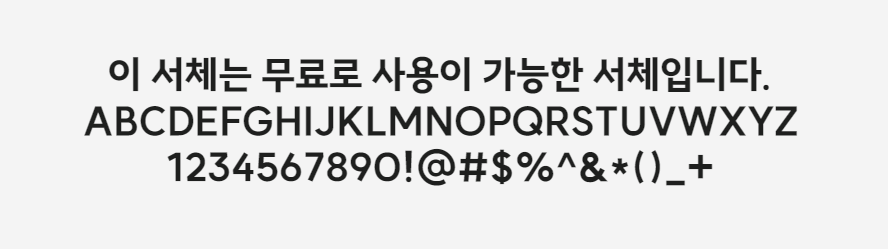
스위트체
스위트체는 현대적인 감각과 높은 가독성을 겸비한 무료 폰트입니다. 디지털 환경에서의 사용자 경험(UX)과 사용자 인터페이스(UI) 디자인에 최적화되어 개발되었으며, 간결하면서도 세련된 디자인이 특징입니다. 이 폰트는 정원, 직각, 직선, 사선 등 기하학적 조형 요소에 집중하여 디자인되었으며, 이는 스위트체가 간결하면서도 명료한 인상을 주는 데 기여합니다.
특히, UI 환경에서 헤드라인 폰트로 사용될 때 시선을 사로잡아 중요한 정보를 효과적으로 전달할 수 있도록 디자인되었습니다. 스위트체는 다양한 디지털 환경에서의 활용성을 고려하여 개발되었으며, 웹사이트, 앱, 디지털 출판물 등 다양한 매체에서 일관되고 세련된 디자인을 유지할 수 있도록 지원합니다.
다양한 크기와 해상도에서도 높은 가독성을 유지하여 사용자가 정보를 쉽고 편안하게 읽을 수 있도록 돕습니다. 스위트체는 현대적인 디자인 트렌드를 반영하면서도 실용성을 잃지 않는 폰트를 찾는 디자이너와 개발자에게 이상적인 선택이 될 것입니다.
폰트의 디자인 특징
스위트체는 기하학적인 형태를 기반으로 디자인되어 간결하고 현대적인 느낌을 줍니다. 정원, 직각, 직선, 사선 등의 요소를 활용하여 디자인되었으며, 이는 폰트에 구조적인 안정감과 명료함을 부여합니다. 디지털 환경에서의 가독성을 높이기 위해 각 글자의 형태와 간격이 세심하게 조정되었습니다.
헤드라인에 사용될 때 시선을 사로잡는 효과가 뛰어나며, 사용자 인터페이스(UI) 디자인에 적합하도록 디자인되었습니다. 스위트체는 다양한 크기와 해상도에서도 높은 가독성을 유지하며, 이는 디지털 환경에서의 활용성을 극대화합니다.
어떤 용도로 사용해볼까요?
스위트체는 현대적이고 세련된 디자인이 필요한 다양한 분야에서 활용될 수 있습니다. 특히, 웹사이트 및 앱 디자인, 디지털 출판물, 광고 및 마케팅 자료, 프레젠테이션 자료 등에 적합합니다. 헤드라인 및 제목에 사용할 경우, 간결하면서도 강렬한 인상을 줄 수 있으며, 본문 텍스트에 사용할 경우, 높은 가독성으로 사용자의 편안한 독서를 돕습니다.
UI 디자인에 적용하여 사용자 경험을 향상시킬 수 있으며, 디지털 환경에서의 가독성이 중요한 디자인 프로젝트에 이상적인 선택입니다. 스위트체는 현대적인 디자인 트렌드를 반영하면서도 실용성을 잃지 않아, 다양한 디자인 프로젝트에서 활용될 수 있습니다.